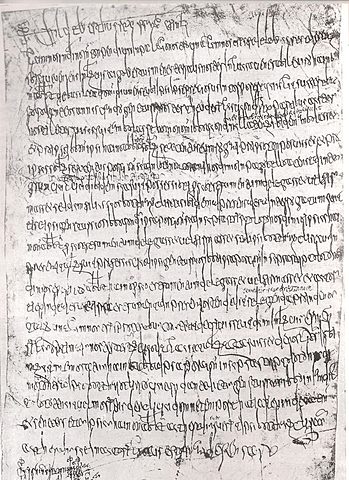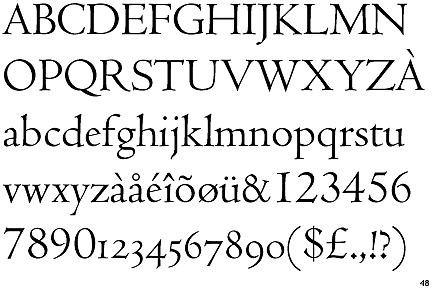
La escritura pictográfica o simplemente pictografía es una forma de comunicación escrita que se remonta al neolítico, donde el hombre usaba las pictografías para representar objetos mediante dibujos en una lámina de piedra. La escritura en piedras es la primera manifestación de la expresión gráfica y se caracteriza porque cada signo del código gráfico es la traducción de una frase o de un enunciado completo.
Frente a los sistemas pictóricos, fonográficos y figurativos que utilizaban los egipcios, aparece un nuevo sistema de escritura mucho más sencillo que pronto se extendería por todo lo ancho y largo del mediterráneo. Un sistema sencillo en el que cada sonido podía ser representado con un sólo signo, al contrario de lo que ocurría con las antiguas escrituras mesopotámicas o egipcias.
Su característica esencial lo constituye la cursiva de modo que es una escritura propiamente minuscula mientras que la uncial es mayúscula.
A partir de entonces y con la practica ya individualizada de la uncial como tipología básica, además de la semiuncial y la capital clásica, ésta irá evolucionando y adquiriendo caracteres propios en cada país e incluso cada scriptorium, ya que con la práctica los monjes irán adquiriendo destrezas e introduciendo sus propios estilos. -
trata de una letra minúscula donde se pierde la proporción y los trazos entre letras y palabras se unen mediante ligaduras. Al ser una letra usada para documentos se prima la rapidez de una escritura que no necesita levantar la pluma del papel para realizar espacios. Reproducimos a continuación un diploma del año 695 del rey Franco Childeberto III y adjuntamos la transcripción en latín de las tres primeras líneas.
. LAS ESCRITURAS PRECAROLINAS La llegada de los árabes le dió unas características peculiares contribuyendo a la formación de la letra. La escritura Ventana apareció en el sur de Italia, nombre que proviene del ducado de Benavente. Su trazado es limpio y elegante y se aplicó tanto a códices como a documentos públicos y particulares.
tribus godas llegadas al mar Negro desde la lejana Suecia penetraron en Capadocia donde hicieron como prisionero a Ulfilas, obispo arriano y erudito que inventó un alfabeto para dar forma escrita. A lo largo de varias generaciones la minúscula carolina (letras independientes, redondeadas y bien definidas, pero lentas de elaborar) fue convirtiéndose en una escritura llena de puntas, ángulos y rasgos verticales, más rápida de escribir y que podía comprimirse a voluntad
cuyo origen debe situarse en un tipo de escritura documental que antes hemos mencionado y que se llama de albalaes, variante muy cursiva y estilizada de la gótica común castellana, que se caracteriza por la presencia de rasgos que envuelven letras o palabras. Es la escritura documental por excelencia en tiempos de los Reyes Católicos se empieza a usar hacia fines del siglo XIV. Se la utilizaba en la Secretaría Real, en el Consejo de Indias y la utilizaron los escribanos de su Majestad
se les dio el nombre de estilo veneciano, pues las principales imprentas italianas que los producían se habían establecido en la ciudad de Venecia. por lo tanto de su denominación Estilo Veneciano, viene dado por Nicolaus Jenson, grabador y tipógrafo francés que desarrolló la mayor parte de su trabajo en la “Serenissima”.Es conocido por haber sido el creador de la primera tipografía romana para impresión, que sirvió de inspiración y fue imitada por maestros impresores
la llamada "humanística" o "bastardilla", nueva clara y luminosa escritura nacida en Florencia cuna del movimiento renacentista como reacción contra la escritura gótica y la influencia monacal y escolástica de la Edad Media nacida de un deseo de los copistas de recuperar la sencillez y la armonía de la carolina (a la que llamaban”litera antiqua”). Extendida rápidamente por toda Italia, pronto llegó a Alemania, Francia o España.
Personaje importante de la épora, Tory fue un reformador de la lengua francesa, incluyendo signos como el apóstrofe, el acento y la cedilla. Su obra más importante e influyente fué Champlefeury publicada en 1529 donde medita sobre la estructura proporción y significado místico de las letras.
la primera tipografía dibujada, grabada y fundida por él mismo en el libro Paraphrasis in Elegantiarum Libros Laurentii Vallae de Erasmo de Rotterdam. Esta tipografía estaba basada en los tipos diseñados por los maestros Nicolas Jenson y Francesco Griffo para el libro De Aetna de Pietro Bembo publicada por Aldus Manutius. La tipografía que diseño para este libro fue bastante popular dentro del gremio de la época